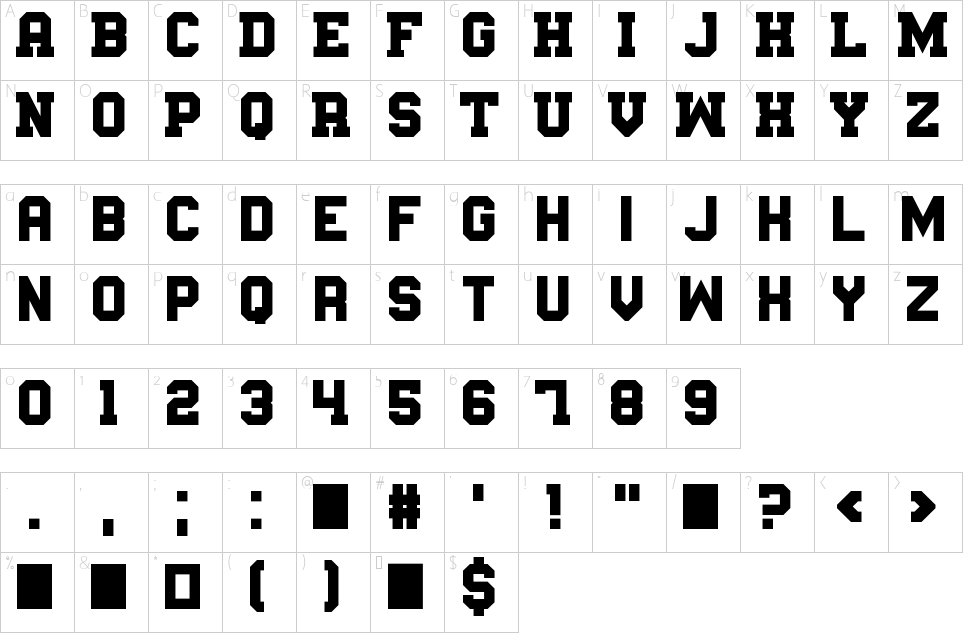
A fonte Messe Muenchen é uma opção elegante e versátil para designers e criativos. Ela foi criada por Chequered Ink e é uma fonte que se encaixa perfeitamente para uso em design gráfico e impressões. Esta fonte gratuita é perfeita para quem busca uma alternativa a fontes de bom gosto e qualidade, sem precisar gastar dinheiro. Com o Messe Muenchen, você pode adicionar um toque sofisticado e profissional a qualquer projeto, seja ele impresso ou digital. Desenvolvida para atender a uma ampla gama de necessidades de design, a Messe Muenchen é uma fonte de alta qualidade disponível para Windows e Mac, e tem sido baixada mais de 12.852 vezes, evidenciando sua popularidade entre designers de todo o mundo.